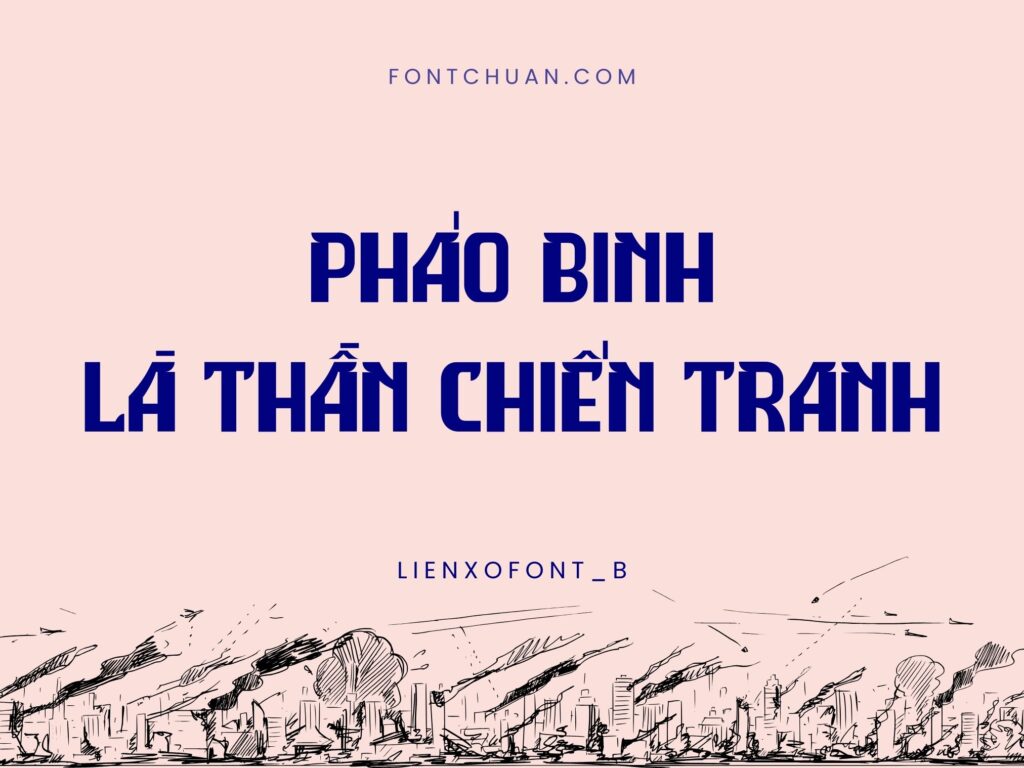
Font Soviet Font Tiếng Việt
Soviet là một Font sans-serif mang phong cách cổ điển, được thiết kế bởi Iconian Fonts. Font này lấy cảm hứng từ kiểu chữ thời kỳ Liên Xô cũ, với các nét chữ đậm và góc cạnh, tạo nên vẻ mạnh mẽ và cứng cáp. Soviet hỗ trợ nhiều ngôn ngữ, bao gồm cả tiếng Việt, và được sưu tầm và đăng bởi thành viên của Font Chuẩn. Nhờ vào đặc trưng hiện đại kết hợp cổ điển, Soviet còn có thể được xem như một Font chữ Công nghệ, phù hợp cho các dự án mang tính sáng tạo và đổi mới.
Font có thiết kế chữ in hoa với các đường nét sắc sảo, phù hợp cho các tiêu đề, poster, logo và các ấn phẩm truyền thông cần sự nổi bật. Các ngành nghề như quảng cáo, công nghệ, giáo dục và bất động sản có thể tận dụng hiệu quả font này. Ngoài ra, Soviet cũng thích hợp cho các sự kiện như lễ hội, sinh nhật, ngày Nhà giáo và Valentine.